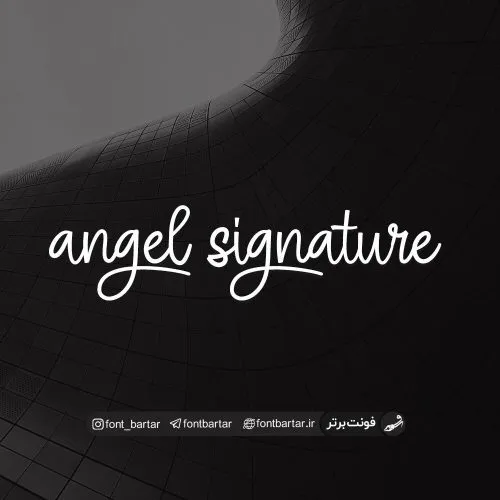
دانلود فونت انگلیسی angel signature
فونت انگلیسی angel signature ، فونت بسیار زیبا و خاص مناسب طراحی لوگو ، ساختار سری فونت های دستنویس را یدک می کشد و چینش فانتزی و گرافیکی دارد ، این فونت زیبا را به هیچ عنوان از دست ندهید.
فونت angel signature مورد استفاده برای:
- طراحان وب سایت و گرافیست های خلاق می توانند از این مجموعه زیبا فونت در طراحی پروژه های تبلیغاتی و تجاری خود کمک بگیرند.